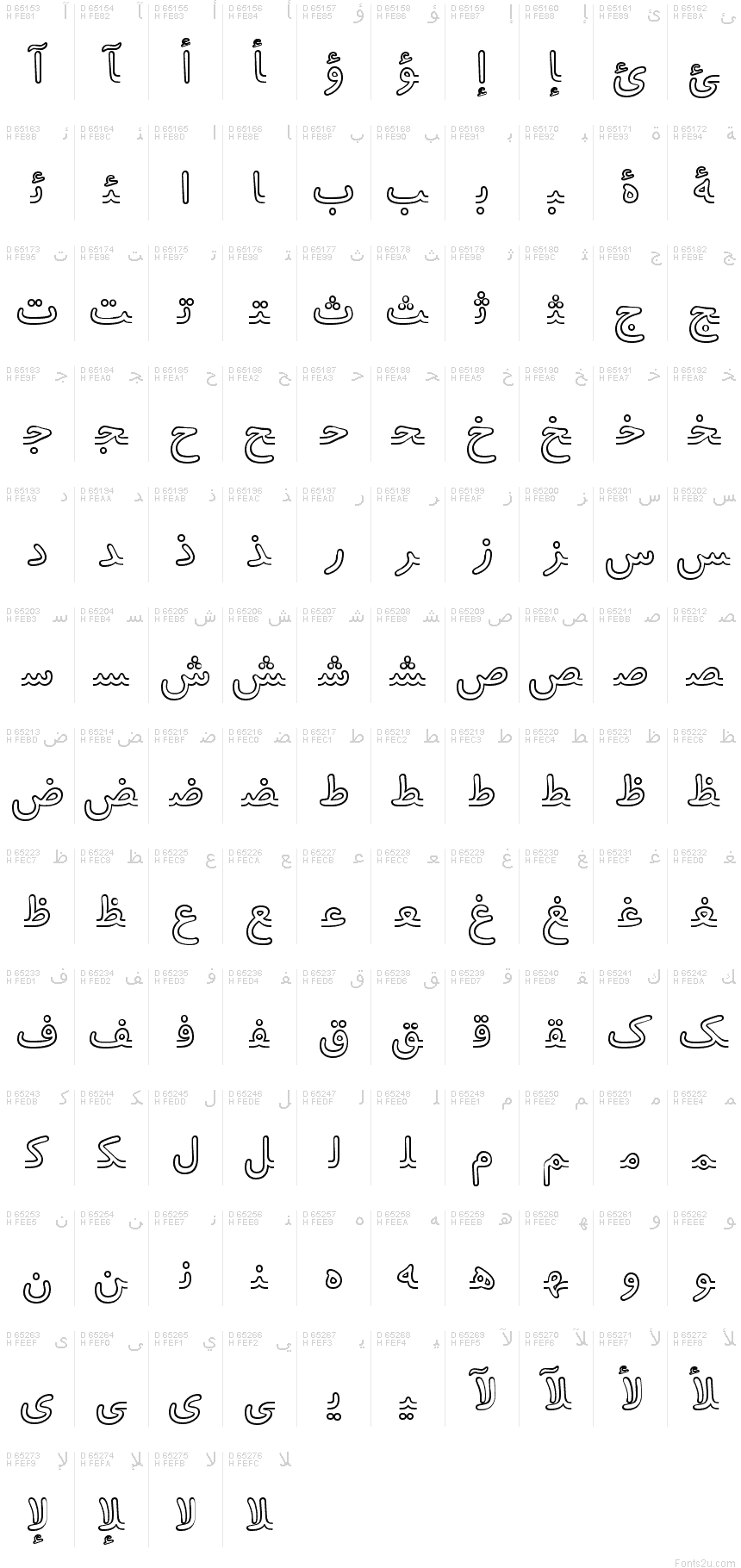
B Koodak Outline je bezplatné arabské obrysové písmo od Borna Rayaneh, které působí přátelským, ručně psaným dojmem. Díky měkkým křivkám a otevřeným tvarům působí lehce, nikoliv formálně. Písmena mají hravý náboj a zaoblený rytmus připomínající školní učebnice, takže styl působí hřejivě a přístupně i navzdory vzdušnému obrysovému provedení.
Toto bezplatné písmo se skvěle hodí na obálky dětských knih, vzdělávací plakáty, obaly, přání a krátké brandingové projekty, kde by arabské písmo mělo působit uvolněně a lidsky. Dobře funguje také u titulků a krátkých popisků, protože obrysová kresba udržuje tvary živé a zároveň kolem nich ponechává dostatek vizuálního prostoru.
B Koodak Outline